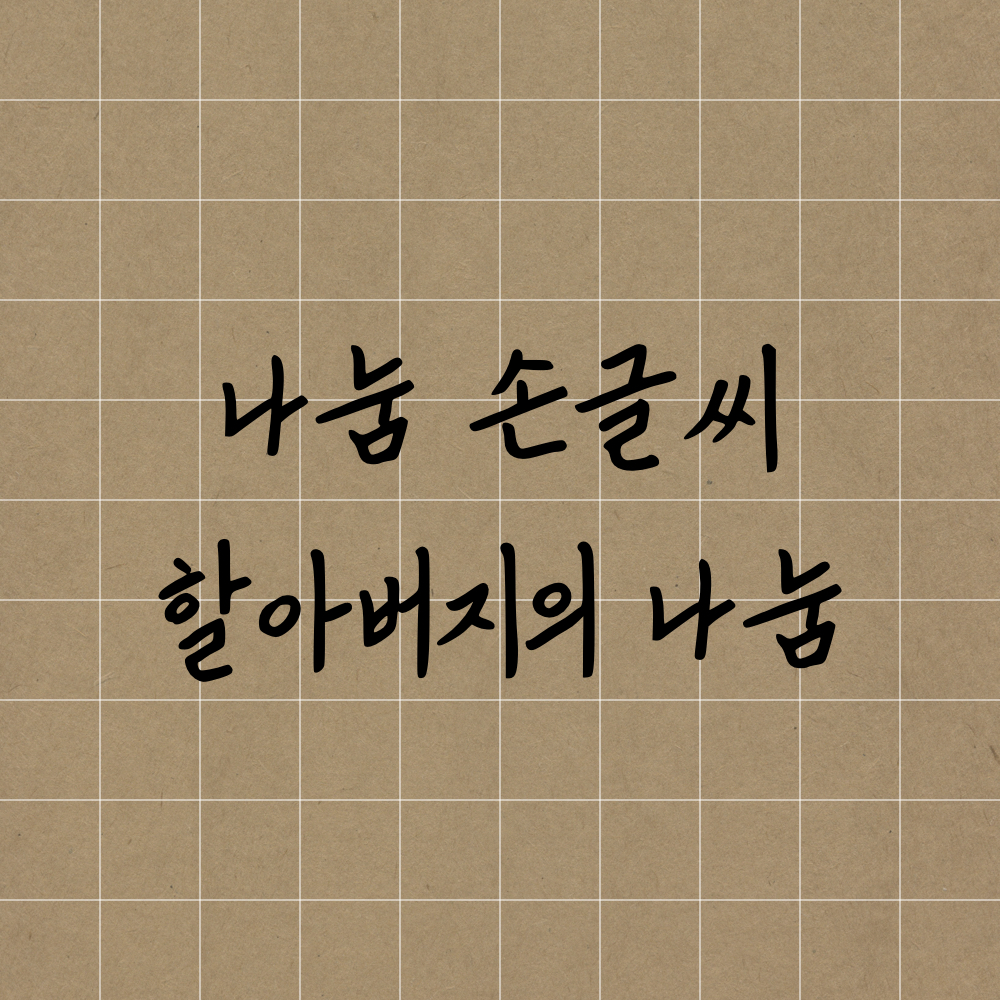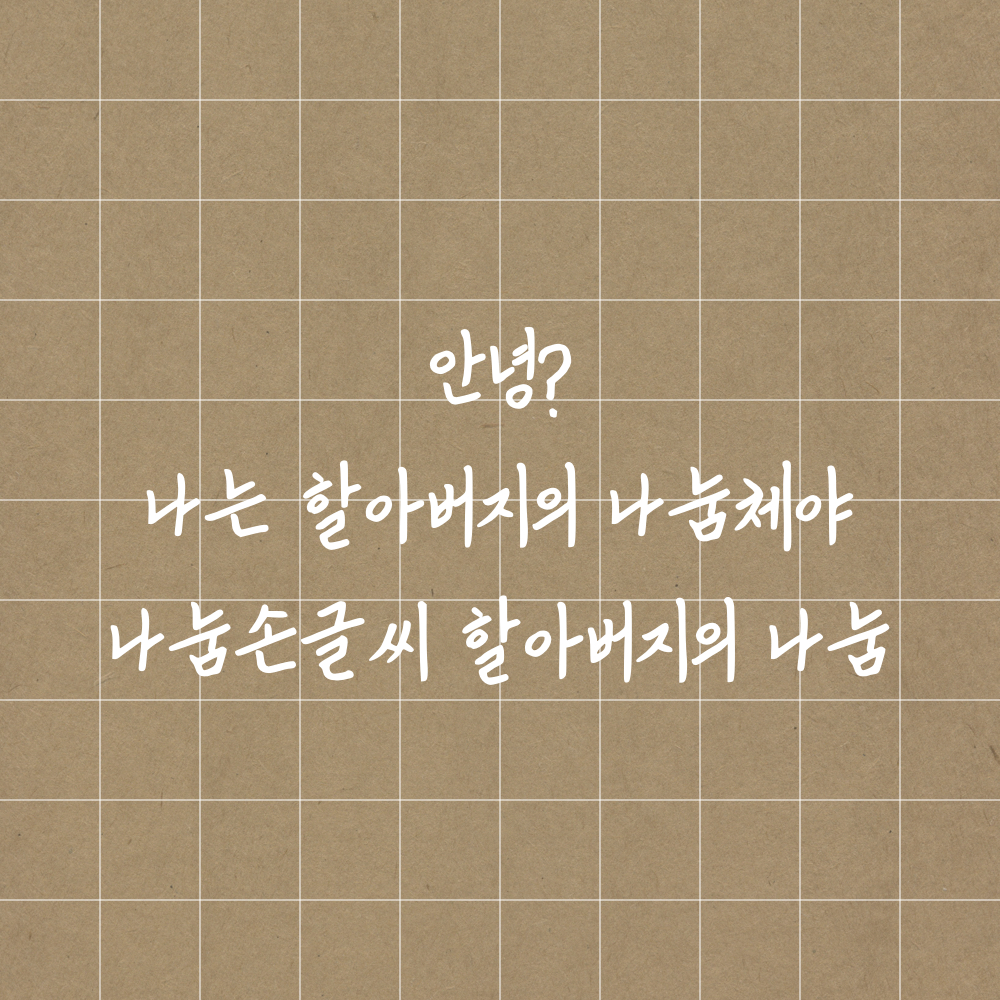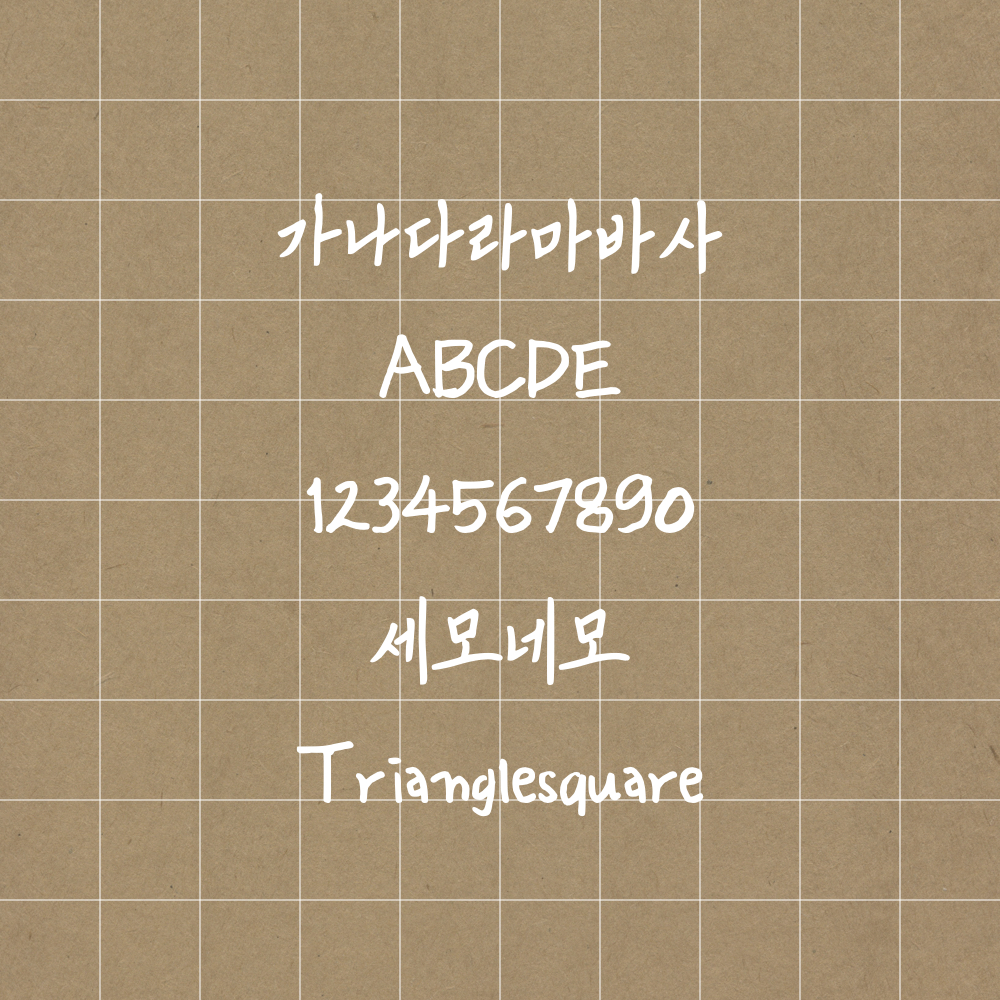
오늘의 폰트는 할아버지의 나눔체입니다💙
드디어 제가 찾고 찾던 글씨체를 찾았습니다. 가지고 있던 폰트와 완전히 다른 재질의 폰트❤️
예시를 살펴볼까요~?🤓
직선이 반듯해서 마음이 편안..💛
전체적으로 글씨의 크기가 일정해서 깔끔한 느낌을 주지만
자음들이 사선으로 표현되어 다른 폰트와 달리 독특한 매력이 있네요💕
다음 다꾸는 할아버지의 나눔체로 해야지~~!!